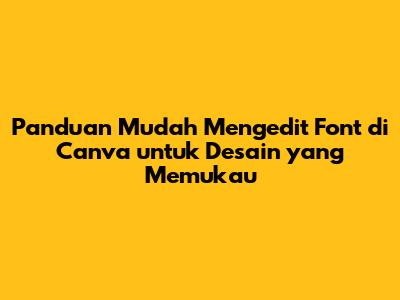
Mengedit font di Canva adalah salah satu keterampilan dasar yang wajib dikuasai bagi siapa saja yang ingin membuat desain visual yang menarik. Canva, sebagai platform desain grafis yang populer, menyediakan berbagai fitur untuk mempermudah pengeditan font, mulai dari mengubah jenis font, ukuran, warna, hingga memberikan efek khusus. Artikel ini akan membahas secara mendalam tentang cara mengedit font di Canva, mulai dari langkah-langkah dasar hingga tips dan trik untuk menciptakan desain yang lebih profesional dan eye-catching. Jadi, buat kalian yang baru mulai atau ingin meningkatkan kemampuan desain di Canva, simak terus panduan lengkap ini!
Memahami Dasar-Dasar Pengeditan Font di Canva
Sebelum kita masuk ke langkah-langkah praktis, mari kita pahami dulu beberapa dasar penting tentang pengeditan font di Canva. Pertama, Canva menawarkan beragam pilihan font yang bisa Anda gunakan. Anda bisa menemukan font yang sesuai dengan gaya desain Anda, mulai dari font serif yang klasik dan elegan, font sans-serif yang modern dan bersih, hingga font script yang artistik dan personal. Untuk mengakses koleksi font Canva, cukup klik pada teks yang ingin Anda edit, lalu pilih opsi font di bilah alat di atas editor. Di sana, Anda bisa melihat daftar font yang tersedia, serta mencari font tertentu berdasarkan nama atau kategori.
Selain memilih jenis font, Anda juga bisa mengatur ukuran font. Ukuran font yang tepat sangat penting untuk memastikan teks mudah dibaca dan proporsional dengan elemen desain lainnya. Canva memungkinkan Anda mengubah ukuran font dengan dua cara: menggunakan menu drop-down ukuran font di bilah alat, atau dengan menyeret ikon pengatur ukuran di sudut kotak teks. Anda juga bisa mengatur gaya font, seperti tebal (bold), miring (italic), atau bergaris bawah (underline), untuk memberikan penekanan pada teks tertentu. Fitur-fitur ini sangat berguna untuk membuat judul, subjudul, atau kutipan yang menonjol dalam desain Anda. Selain itu, Canva juga menyediakan fitur perataan teks (rata kiri, rata tengah, rata kanan, atau rata kiri-kanan) untuk mengatur tampilan teks agar sesuai dengan tata letak desain.
Terakhir, jangan lupakan pentingnya warna font. Warna font dapat menciptakan suasana yang berbeda dalam desain Anda, serta membantu membedakan teks dengan latar belakang. Canva menyediakan palet warna yang luas, termasuk warna-warna standar, warna merek (jika Anda bekerja untuk suatu merek), dan opsi untuk memasukkan kode warna HEX. Anda juga bisa menggunakan fitur 'efek' untuk menambahkan efek visual pada teks, seperti bayangan, outline, atau efek melengkung. Dengan memahami dasar-dasar ini, Anda akan lebih siap untuk menjelajahi berbagai fitur pengeditan font di Canva dan menciptakan desain yang lebih kreatif.
Langkah-Langkah Mengedit Font di Canva:
Sekarang, mari kita masuk ke langkah-langkah praktis mengedit font di Canva. Prosesnya sebenarnya cukup mudah dan intuitif, bahkan bagi pemula sekalipun. Pertama, buka desain Anda di Canva. Jika Anda belum memiliki desain, Anda bisa membuat desain baru dari template yang tersedia atau membuat desain kosong. Setelah desain terbuka, pilih elemen teks yang ingin Anda edit. Jika Anda ingin menambahkan teks baru, klik ikon teks di bilah alat sebelah kiri, lalu pilih opsi 'tambahkan judul', 'tambahkan subjudul', atau 'tambahkan isi teks'.
Setelah elemen teks terpilih, Anda akan melihat bilah alat pengeditan di atas editor. Di bilah alat ini, Anda bisa menemukan berbagai opsi untuk mengedit font. Untuk mengubah jenis font, klik pada nama font saat ini (biasanya muncul sebagai nama font default, seperti 'Open Sans' atau 'Lato'). Kemudian, pilih font yang Anda inginkan dari daftar yang muncul. Anda bisa menggulir daftar untuk melihat semua opsi, atau mengetikkan nama font di kotak pencarian untuk menemukan font tertentu. Jika Anda tidak menemukan font yang Anda cari, Anda bisa mengunggah font kustom (khusus untuk pengguna Canva Pro).
Selanjutnya, atur ukuran font sesuai kebutuhan. Klik pada menu drop-down ukuran font di bilah alat, lalu pilih ukuran yang Anda inginkan. Anda juga bisa mengetikkan ukuran font secara manual di kotak yang tersedia. Untuk memberikan penekanan pada teks, gunakan opsi gaya font (tebal, miring, atau bergaris bawah). Klik ikon 'B' untuk menebalkan teks, ikon 'I' untuk memiringkan teks, dan ikon 'U' untuk memberikan garis bawah pada teks. Gunakan fitur perataan teks untuk mengatur tampilan teks (rata kiri, rata tengah, rata kanan, atau rata kiri-kanan). Terakhir, atur warna font dengan mengklik ikon warna di bilah alat dan memilih warna yang Anda inginkan dari palet warna. Dengan mengikuti langkah-langkah ini, Anda bisa dengan mudah mengedit font di Canva dan menciptakan desain yang sesuai dengan visi Anda.
Tips dan Trik untuk Pengeditan Font yang Lebih Profesional
Setelah memahami dasar-dasar dan langkah-langkah pengeditan font, mari kita bahas beberapa tips dan trik untuk menciptakan desain yang lebih profesional dengan font di Canva. Pertama, pilih kombinasi font yang tepat. Jangan gunakan terlalu banyak jenis font dalam satu desain, karena dapat membuat desain terlihat berantakan dan sulit dibaca. Sebaiknya, gunakan maksimal dua atau tiga jenis font yang saling melengkapi. Misalnya, Anda bisa menggunakan satu font untuk judul dan subjudul, dan font lain untuk isi teks.
Perhatikan hierarki visual. Gunakan ukuran font, gaya font (tebal, miring), dan warna untuk menciptakan hierarki visual yang jelas. Judul harus lebih besar dan lebih menonjol daripada subjudul, dan subjudul harus lebih menonjol daripada isi teks. Gunakan warna yang berbeda untuk membedakan elemen-elemen desain. Pertimbangkan keterbacaan. Pastikan teks mudah dibaca, terutama jika desain Anda berisi banyak teks. Pilih font yang mudah dibaca, hindari penggunaan font yang terlalu rumit atau dekoratif untuk isi teks. Perhatikan jarak antar huruf (kerning), jarak antar baris (leading), dan jarak antar paragraf (spacing) untuk meningkatkan keterbacaan.
Gunakan efek teks dengan bijak. Canva menyediakan berbagai efek teks, seperti bayangan, outline, dan efek melengkung. Gunakan efek ini untuk memberikan sentuhan kreatif pada desain Anda, tetapi jangan berlebihan. Terlalu banyak efek teks dapat membuat desain terlihat berlebihan dan mengganggu. Sesuaikan font dengan tema desain. Pilih font yang sesuai dengan tema desain Anda. Misalnya, gunakan font yang lebih formal dan elegan untuk desain bisnis, dan font yang lebih ceria dan playful untuk desain anak-anak. Eksperimen dan berani mencoba. Jangan takut untuk bereksperimen dengan berbagai kombinasi font, ukuran, warna, dan efek. Coba berbagai macam variasi untuk menemukan gaya desain yang paling sesuai dengan Anda.